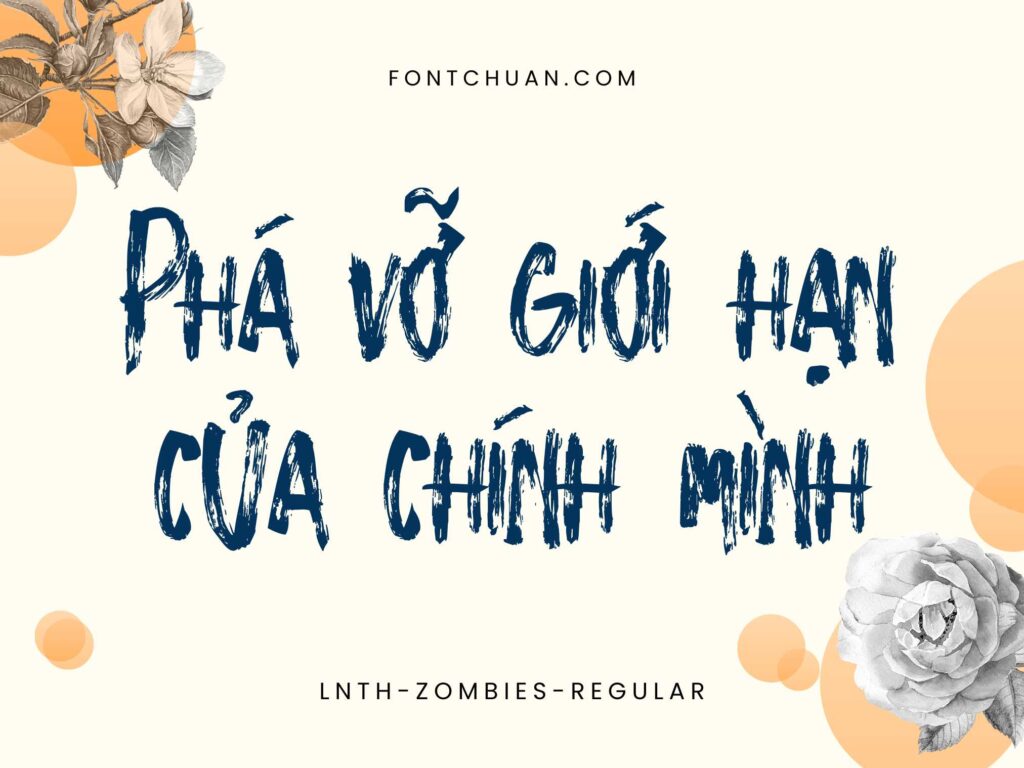
Font LNTH Zombies Việt Hóa
Font Zombies là một font chữ độc đáo mang phong cách kinh dị, đồng thời là một trong các kiểu Font Gothic, được thiết kế với các nét chữ méo mó, gồ ghề, tạo cảm giác rùng rợn. Font này thường được sử dụng trong các thiết kế chủ đề Halloween, truyện tranh kinh dị, poster phim hoặc các sự kiện ma quái. Với đường nét thô ráp, độ dày trung bình và sự ngẫu nhiên trong từng ký tự, Zombies mang lại một ấn tượng mạnh mẽ, phù hợp cho các tiêu đề và thiết kế mang phong cách huyền bí.
Phiên bản này đã được Việt hóa bởi LNTH, hỗ trợ đầy đủ tiếng Việt cùng hơn 50 ngôn ngữ khác, giúp người dùng dễ dàng ứng dụng trong thiết kế quốc tế. Font Zombies được các thành viên Font Chuẩn sưu tầm và đăng tải nhằm đáp ứng nhu cầu tìm kiếm font chữ mang phong cách rùng rợn, đặc biệt phù hợp với các dự án sáng tạo cần yếu tố bí ẩn và nổi bật.
Về đặc điểm thiết kế, Zombies có các đường nét méo mó, cấu trúc chữ không đồng đều, tạo cảm giác kỳ quái. Font này đặc biệt thích hợp để sử dụng trong các tiêu đề lớn, thiết kế banner, áp phích hoặc các sản phẩm truyền thông có yếu tố kinh dị. Nhờ sự phá cách độc đáo, nó cũng phù hợp với thiết kế mang phong cách cổ điển, bí ẩn.
Font Zombies được ứng dụng rộng rãi trong các sự kiện như Halloween, lễ hội kinh dị. Nó phù hợp với nhiều ngành nghề như quảng cáo, thiết kế đồ họa, in ấn sáng tạo, trang trí lễ hội và các sản phẩm truyền thông đặc biệt.